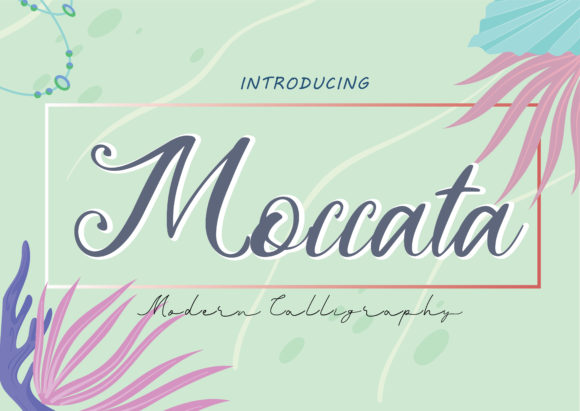
è¸�入缤纷绚烂的Moccataå—体世界——一款é�žå‡¡çš„脚本å—体,将优雅与活力èž�ä¸ºä¸€ä½“ã€‚è¿™ç‹¬ä¸€æ— äºŒçš„å—体以其ç�µåŠ¨é£˜é€¸çš„ç¬”è§¦å’Œä¼˜é›…å¦©åªšçš„æ›²çº¿ï¼Œè®©ä½ åœ¨è‰ºæœ¯çš„æµ·æ´‹ä¸å°½æƒ…徜徉。
Moccata的创作ç�µæ„Ÿæº�于自然界的美妙律动,笔触间ç�µå·§è½»ç›ˆï¼Œä»¿ä½›éš�é£Žèµ·èˆžçš„èŠ±ç“£ï¼Œä¸ºä½ çš„è®¾è®¡å¢žæ·»ç›Žç„¶ç”Ÿæœºã€‚ä½¿ç”¨Moccata,仿佛将大自然的ç�µåŠ¨æ°”æ�¯èž�å…¥ä½ çš„ä½œå“�ä¸ã€‚
æ— è®ºä½ æƒ³ä¸ºä½ çš„YouTube频é�“æ‰“é€ å¤ºäººçœ¼ç�ƒçš„è‰ºæœ¯æµ·æŠ¥ï¼Œè¿˜æ˜¯ä¸ºä½ çš„å�šå®¢æ–‡ç« 增添一抹ç�µåŠ¨æ°”æ�¯ï¼ŒMoccataéƒ½èƒ½æ»¡è¶³ä½ çš„éœ€æ±‚ã€‚å®ƒé‚£æ¸…æ–°è„±ä¿—çš„å—体设计,ä¸�仅能够为设计增添一抹创æ„�,更能折射出设计师独特的艺术å“�味。
用Moccataæ¼”ç»Žä½ çš„åˆ›æ„�世界,它那优美潇洒的笔触,宛如行云æµ�æ°´ï¼Œè‡ªç”±æŒ¥æ´’ï¼Œå®šèƒ½è®©ä½ åœ¨è‰ºæœ¯åˆ›ä½œä¸æ¸¸åˆƒæœ‰ä½™ï¼Œç»½æ”¾å‡ºå¤ºç›®çš„å…‰å½©ã€‚æ— è®ºä½ æ˜¯èº«ç»�百战的设计师,还是åˆ�涉设计领域的爱好者,Moccata都能æˆ�ä¸ºä½ åˆ›ä½œè·¯ä¸Šçš„å�¯é� 伙伴。
拥抱Moccata,让å—体æˆ�ä¸ºä½ çš„è‰ºæœ¯ç”»ç¬”ï¼Œè®©åˆ›æ„�如潮水般涌现。它那é�žå‡¡çš„è‰ºæœ¯æ„ŸæŸ“åŠ›ï¼Œå°†ä¸ºä½ çš„è®¾è®¡ä½œå“�注入ç�µé‚,令平凡的设计幻化æˆ�ç�µåŠ¨çš„è‰ºæœ¯å“�。准备好在Moccataçš„æ€€æŠ±ä¸æ”¾é£žä½ 的想象,è§�è¯�å—体艺术的奇迹å�§ï¼�